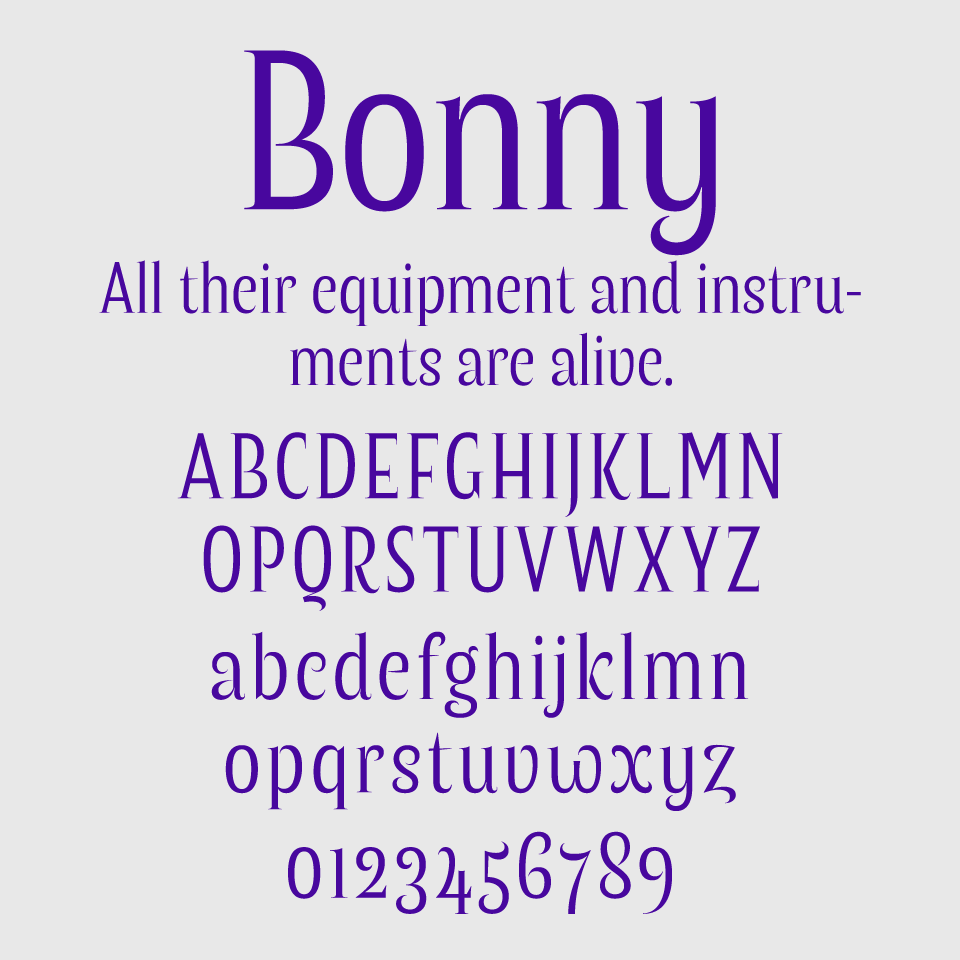
Bonnyフォントは、クラシカルなセリフ体に、ほのかに女性らしさや柔らかさをまとわせたデザインが特徴です。縦にスラリと伸びるプロポーションと、さりげない装飾的な端の処理が、気品と清潔感を両立させているデザインがとっても素敵です。
伝統的な書体に現代の空気を加えたような佇まいで、洗練されたテキスト表現を求める場面に適しています。上品ながらも親しみやすく、ブライダルやコスメなど、ややフェミニンな世界観とも相性の良いフォントです。